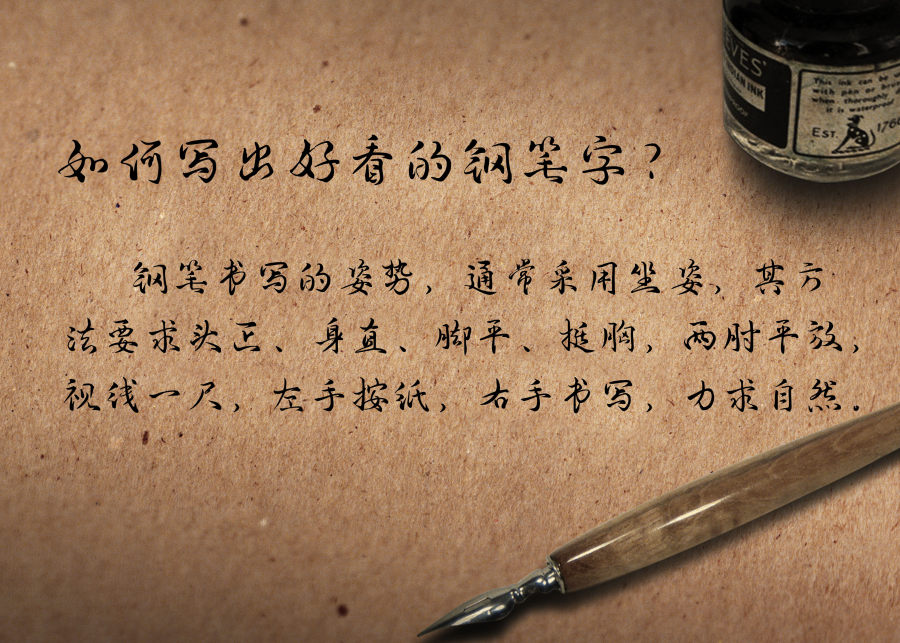
不知道各位小伙伴是否听说过庞中华的行书字体呢?其实这是一种最新推出的手机上的一种字体,我们不知道很正常,今天小编就带你们来如何进行庞中华行书字体下载,一起来学习一下吧。
庞中华行书是一种适合我们安卓手机系统的程序字体,没见过的小伙伴不要担心。庞中华是我们国家的一个书法家,他从小就开始学习书法,在二十世纪后期过程时发行了自己的一个字帖,直到现在一共出版了一百多中字帖,是一个伟大的书法家。